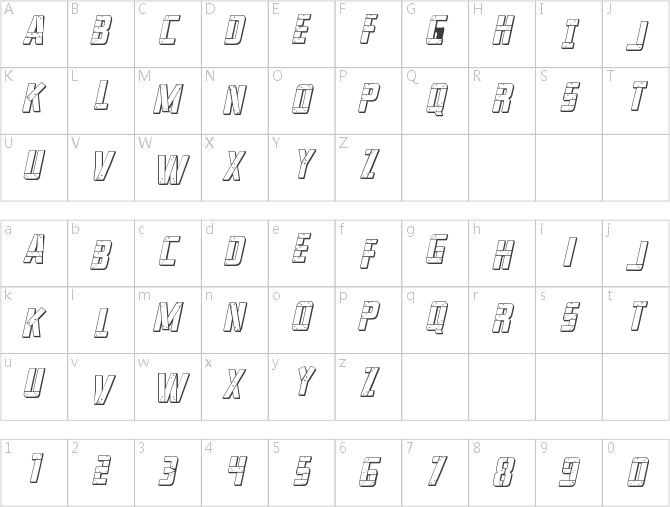
Frank-n-Plank 3D Italic
Frank-n-Plank 3D Italic介紹
Frank-n-Plank 3D Italic字體字庫是一款讓人賞心悅目、百看不厭的英文字體,適合各類廣告和產品包裝設計應用,字體大小0.13MB,格式為ttf字體,上傳用戶是黃肖,作者/版權方為未知